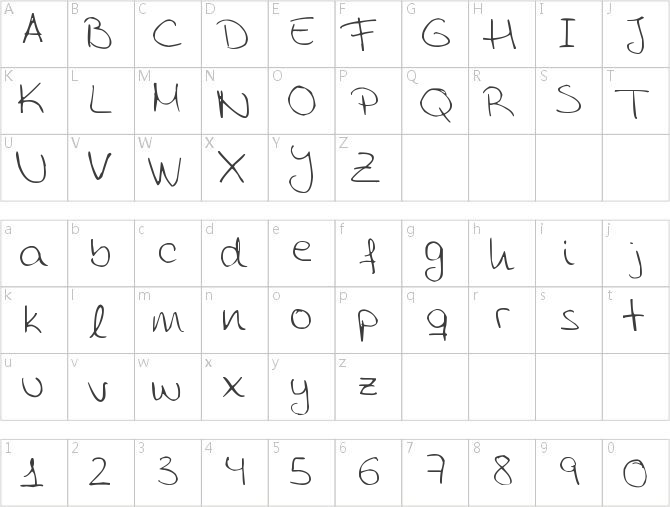
Aida Garmo - Scrap Rounded
Aida Garmo - Scrap Rounded介紹
Aida Garmo - Scrap Rounded字體字庫是一款讓人賞心悅目、百看不厭的英文字體,適合各類廣告和產品包裝設計應用,字體大小0.03MB,格式為ttf字體,上傳用戶是洛洛,作者/版權方為未知